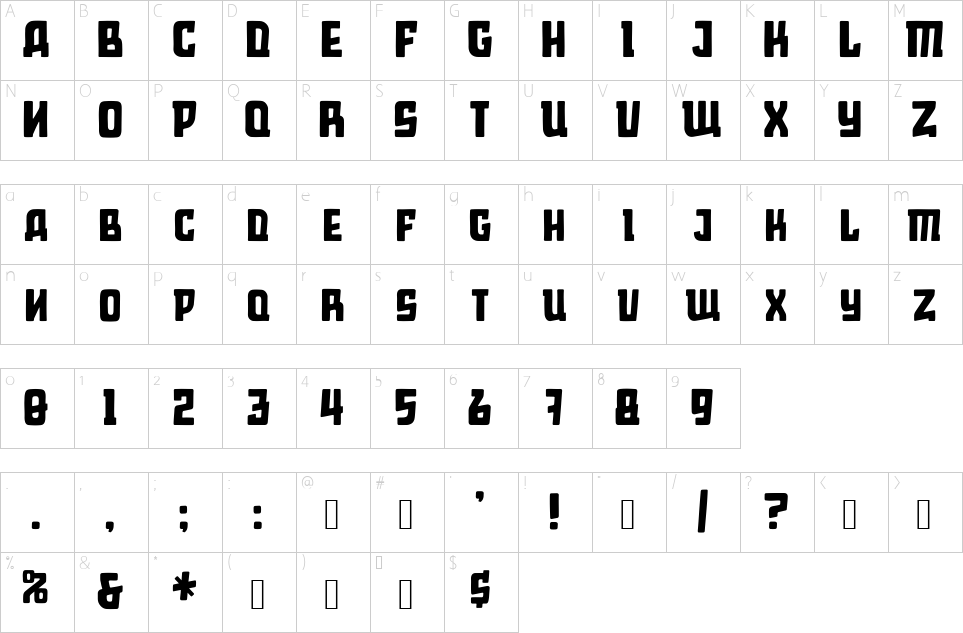
Moscow Mule Font é uma elegante e sofisticada opção para designers gráficos que buscam uma fonte com um toque de originalidade. Desenvolvida por Matt W, a fonte incorpora elementos minimalistas e modernos que podem se destacar em qualquer projeto de design. Com seu design cuidadosamente pensado e sua simplicidade, a Moscow Mule Font é perfeita para adicionar um toque diferenciado a qualquer tipo de projeto. Com versões disponíveis tanto para Windows quanto para Mac, é uma escolha versátil que pode ser usada em diversos ambientes de design. A fonte já foi baixada por 9.176 usuários, o que mostra a sua popularidade e qualidade. Para designers que buscam adicionar um toque único e moderno a suas criações, esta fonte é uma ótima opção.